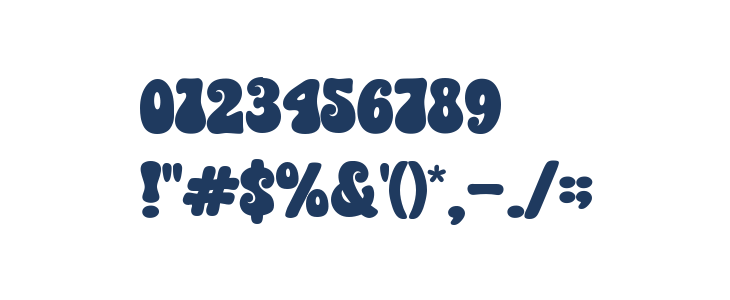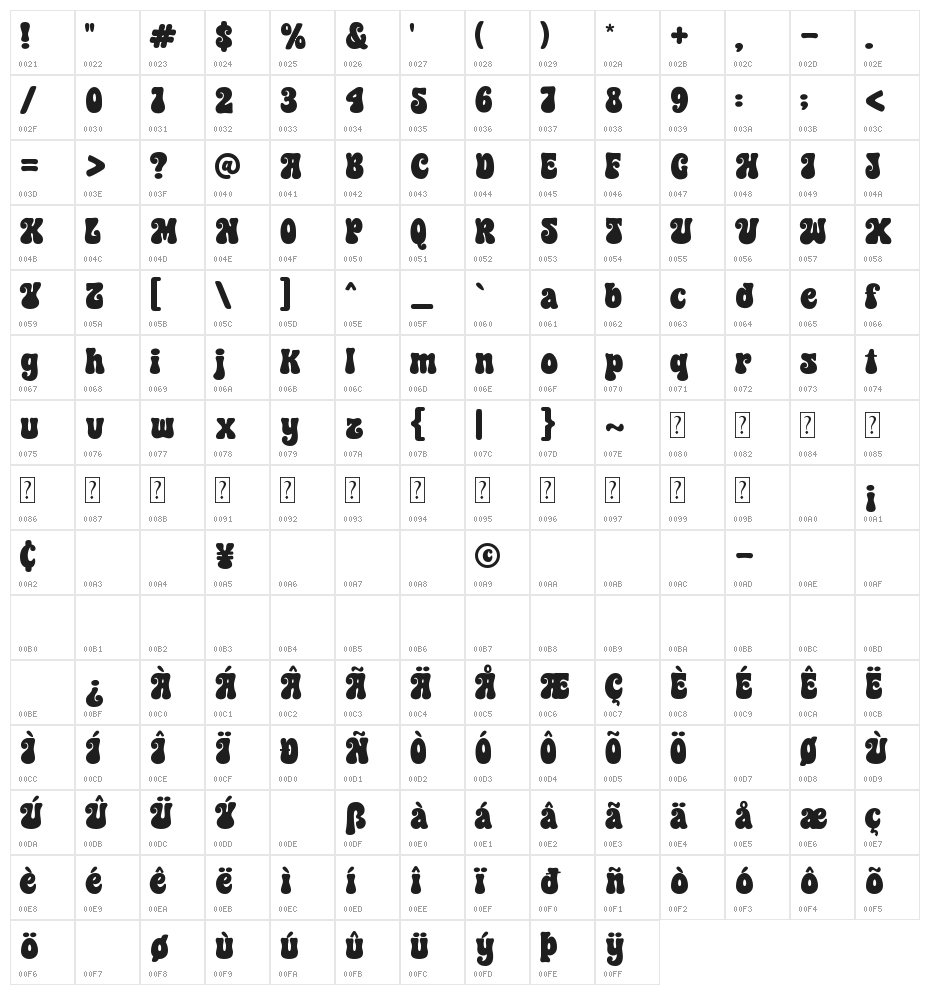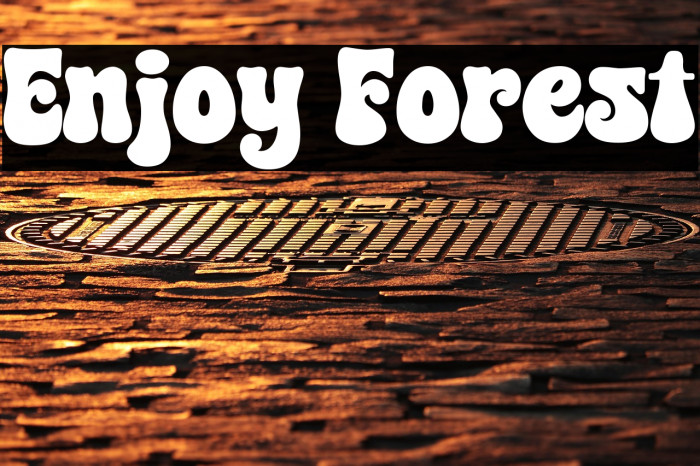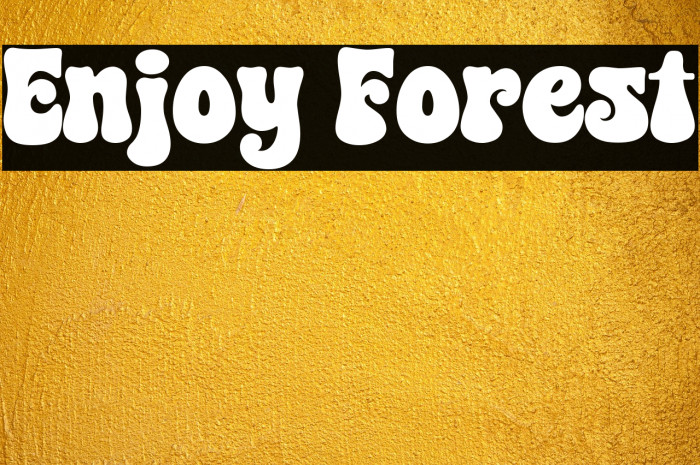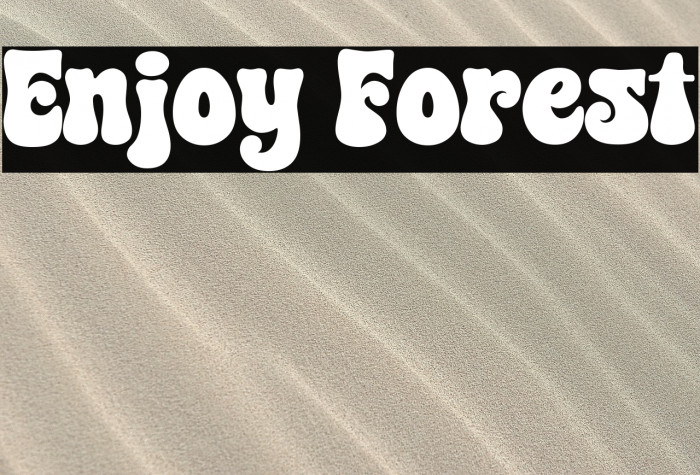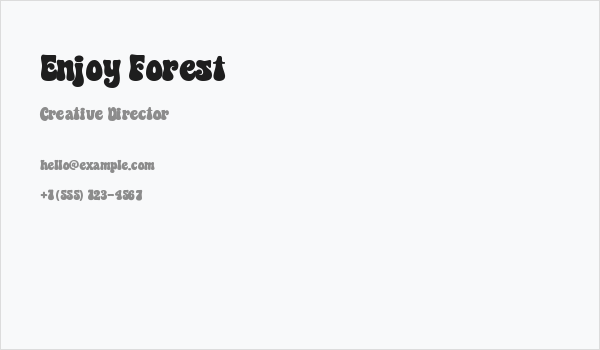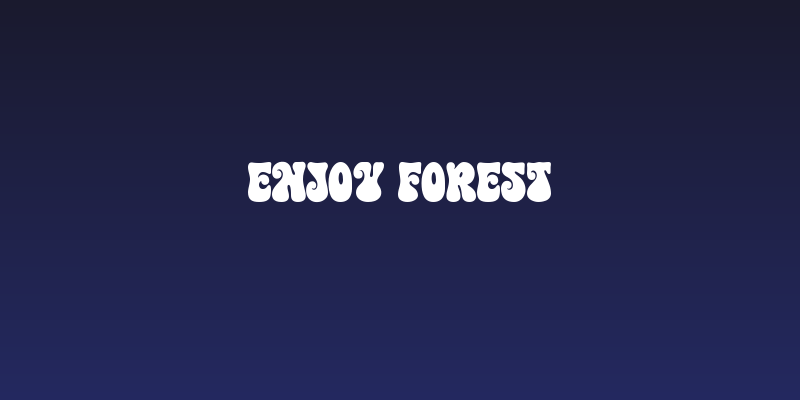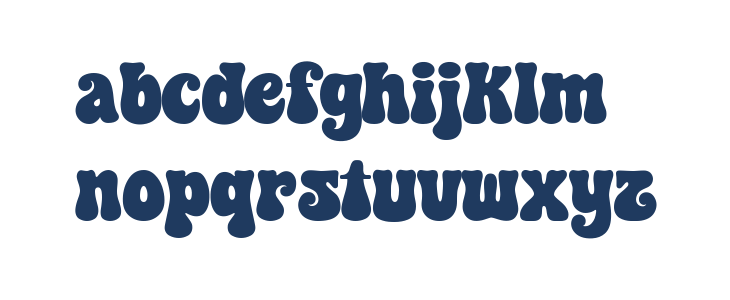
Enjoy Forest Font
| Gesamtstil | Retro, Playful |
| Anwendungsfall | Logos, Posters, Headlines |
| Vorgeschlagene Projekte | Ideal for children's books, playful branding, retro-themed designs, and event posters. |